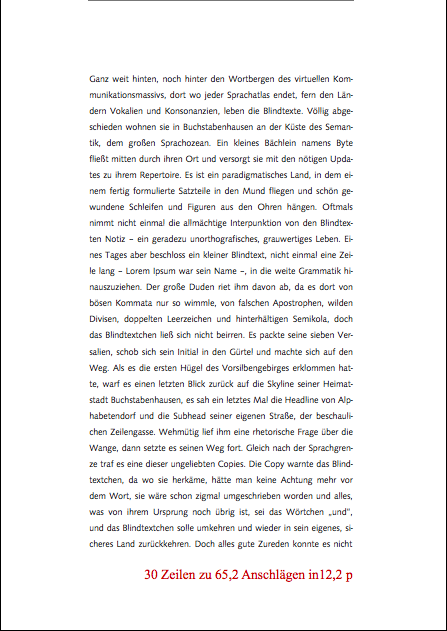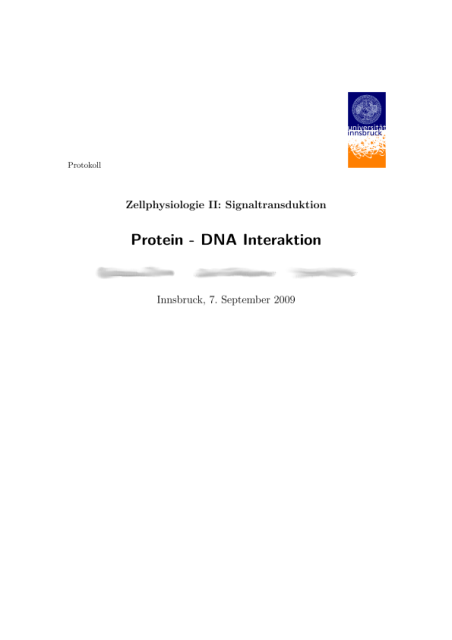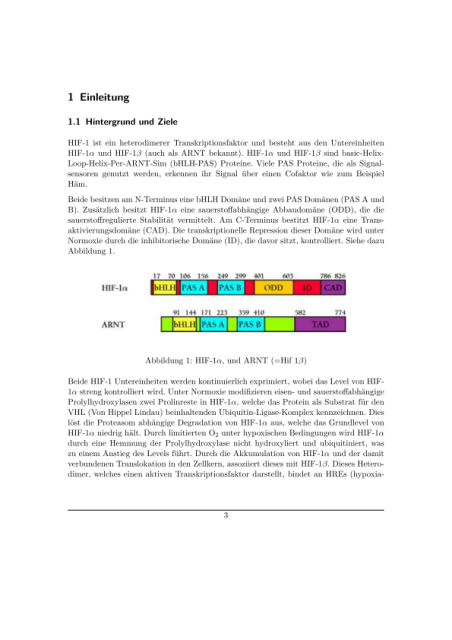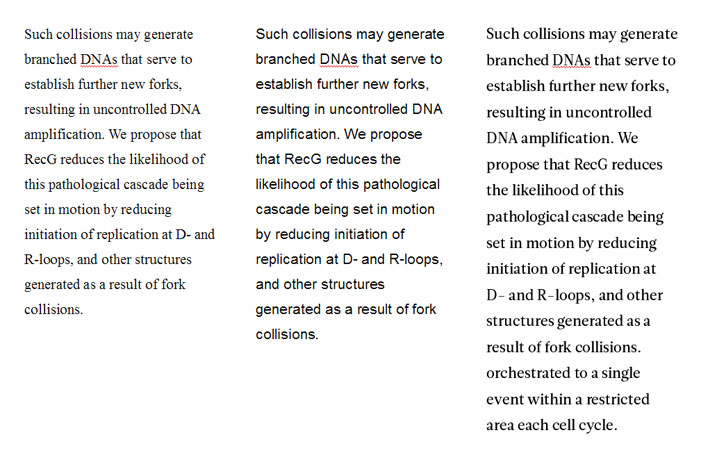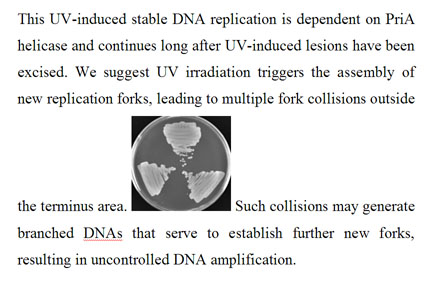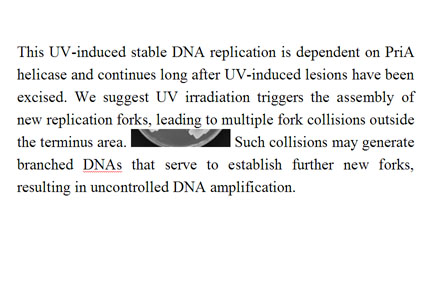
Wissenschaftliche Arbeiten
ich wäre dankbar um jede Meinung zu dem Thema, da ich mich gerne einer Diskussion stellen möchte. Und zwar möchte ich mit der Dozentin sprechen, die bei uns Bioinformatik unterrichtet. Sie hat den Studenten eingebläut, wie ein wissenschaftliches Dokument auszusehen hat. Vor allem am Zeilenabstand möchte ich mich hier aufhängen. Es kam nämlich wieder die Meldung: In wissenschaftlichen Arbeiten verwendet man einen Zeilenabstand von 1,5.
Nun würde mich dazu mal das wichtigste interessiere: Ist das tatsächlich irgendwo so festgesetzt?
Und dann würden mich einfach noch generelle Meinungen dazu interessieren. Interessant fand ich ja auch noch, dass der Dozent bei seiner Vorführung den Zeilenabstand in Word setzte... So viel ich weiß hat Word eine andere Interpretation vom Zeilenabstand?
Sollte das nicht begründet sein regt es mich einfach ein wenig auf. Denn Studenten, die meiner Meinung nach das einfach richtige tun und die Typografie Latex überlassen (warum sich auch selbst mit diesem heiklen Thema auseinander setzen, wenn es diese Software so vorbildlich erledigt) werden damit bestraft.
PS: Ach ja, diese 1,5 sollen ja aus der Schreibmaschinenzeit kommen. Warum war das damals so?
die angabe ›1,5-facher zeilenabstand‹ ist nicht sonderlich präzise, das stimmt. aber: sie verhindert, dass die zeilen sehr eng beeinander stehen, was – angesichts der ohnehin häu?g langen zeilen – wohl das größere übel wäre als zu weiter zeilenabstand (bei vielen alten schreibmaschinen hatte man tatsächlich nicht mehr als diese zwei einstellungen zur auswahl). außerdem kann man bei anderthalbfachem zeilenabstand leichter zwischen den zeilen anmerkungen anbringen, wenn der platz am rechten rand nicht ausreicht. bedenke, dass uni-arbeiten nur manuskripte sind, die noch korrigiert werden – und nicht fertige texte, die für nur-leser in form gebracht werden. darüber hinaus verstehen die meisten sowieso nicht, was gemeint ist, wenn man darauf hinweist, dass es zumindest ästhetisch ansprechender ist, den zeilenabstand auf die schriftart und deren proportionen (›wieso? ich nehme immer times new roman!‹) sowie die schriftgröße (›aber es sind doch 12pt vorgeschrieben.‹) abzustimmen.
ich würde diese weitgehend willkürliche festlegung daher an deiner stelle hinnehmen oder allenfalls stillschweigend ignorieren. du kannst auch mit deiner dozentin darüber diskutieren, nur wird sie wenig von typogra?e verstehen, und erfahrungsgemäß führt ahnungslosigkeit oft zu einem umso heftigeren beharren auf der eigenen position. vielleicht kannst du sie dazu kriegen, den umfang der arbeit in wörtern oder zeichen anzugeben, wie das an etwas progressiveren hochschulen üblich ist, und dir die formatierung freizustellen. versuch’s …
ich denke auch, dass es weniger um Typo geht, als um Gleichbehandlung. Wenn klar ist, dass 30 Seiten abgegeben werden sollen, soll das ein verbindlicher Umfang für alle sein. Times ist gar nicht gut für so lange Zeilen, aber den Standard wird man so schnell nicht kippen können, auch wenn Word seit Langem die Zeichen zählen kann.
Biete doch Georgia mit 1,4 fachem Zeilenabstand an, dann müsste die gleiche Menge Text auf der Seite unterzubringen sein. Und du hast Mediävalziffern - hähä.
Danke für eure Antworten. Also ist der einzige Grund, wie ich raus lese, dass die Länge abgeschätzt werden kann? Es wurde nämlich mehr als optische, typografische wissenschaftliche Richtlinie verkauft, also generell für wissenschaftliche Arbeiten, nicht nur für Arbeiten, die benotet werden.
ich denke auch, dass es weniger um Typo geht, als um Gleichbehandlung.
ja, um gleichbehandlung und, wie ich anzudeuten versucht habe, wahrscheinlich auch darum, das schlimmste für den korrektor (kompress in 14pt comic sans) zu verhindern. eine vorschrift, die irgendwie ästhetisch begründet wäre, ist das meiner ansicht nach nicht. wenn man sich professionell gesetzte wissenschaftliche literatur anschaut, sind 12pt-tnr-exzesse mit großem zeilenabstand doch eher selten zu sehen. die ?ndet man komischerweise nur in manuskripten, bei denen der autor selbst hand angelegt hat.
Biete doch Georgia mit 1,4 fachem Zeilenabstand an, dann müsste die gleiche Menge Text auf der Seite unterzubringen sein. Und du hast Mediävalziffern - hähä.
davon würde ich aus zwei gründen abraten: erstens sollte man sich gar nicht auf eine inhaltliche diskussion einlassen, wenn auf der anderen seite vermutlich kaum fachwissen wartet. wenn man der dozentin verklickert, dass man ein anderes programm verwendet und lieber mit wort-/zeichenzahlen arbeiten würde, kann man eventuell etwas erreichen, sonst eher nicht. zweitens verfügt die georgia (leider!) über keinerlei kerning-informationen, was vor allem im gedruckten einsatz eher hässlich wirken könnte. als alternative könnte ich mir die ebenfalls kostenlose droid serif oder die vista-schrift constantia vorstellen.
Thierry, im Prinzip hast Du recht, aber wie soll man sonst gegen den Wildwuchs gerade im wissenschaftlichen Bereich angehen? Wenn es wirklich um das Volumen ginge, dann müßte man tatsächlich genauere Angaben machen, wie es z.B. bei den Juristen üblich ist. Hier sind der Zeilenabstand, die Schriftgröße, die Schriftart und die Seitenränder genau definiert. Damit läßt sich dann auch die Textmenge vergleichen. Ansonsten geht das einfach nicht:
Alle Schriften erfüllen die Parameter 1,5facher Zeilenabstand und 12 pt. Ein Vergleich der Textmenge ist überhaupt nicht möglich.
Weiterhin ist 1,5facher Zeilenabstand für Korrekturen zwischen den Zeilen einfach viel zu eng, da kriegt man überhaupt keine Korrekturen unter! Selbst bei doppeltem Zeilenabstand wird das schon schwierig, wenn es mal nicht nur um kleine Fehler geht. Der äußere Rand ist also viel wichtiger als der Zeilenabstand, auf den legt aber normalerweise niemand großen Wert
Zur Serifenlosen kann ich nicht viel sagen, ich bin da voreingenommen, ich kriege einfach Augenkrebs wenn ich sie sehe. Wobei ich allerdings auch absolut kein Freund der Computer-Modern-Familie bin. Die echten Typografen hier werden Dir mehr sagen können! :bow: